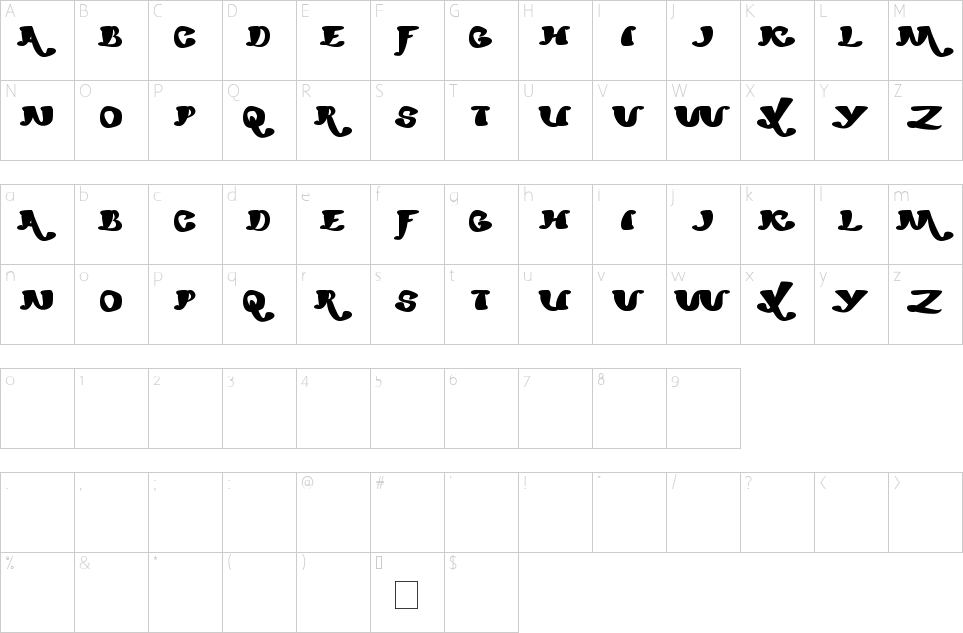
A fonte Mexicano Chili Sauce é uma ótima adição à sua coleção de fontes, fornecendo um toque vibrante e colorido para seus projetos digitais. Desenvolvida por weknow, esta fonte leva um toque exótico e encantador que combina perfeitamente com qualquer design culinário ou cozinha. Com um design moderno e arredondado, ela tem um aspecto atraente que não apenas brilha em uma aplicação de culinária, mas também em outros projetos gráficos que desejam transmitir um estilo único e original. Os usuários já baixaram 8,023 vezes esta fonte, o que comprova o seu valor e popularidade. Adicione esta fonte ao seu arsenal de fontes e permita que ela traga vida a seus projetos digitais.